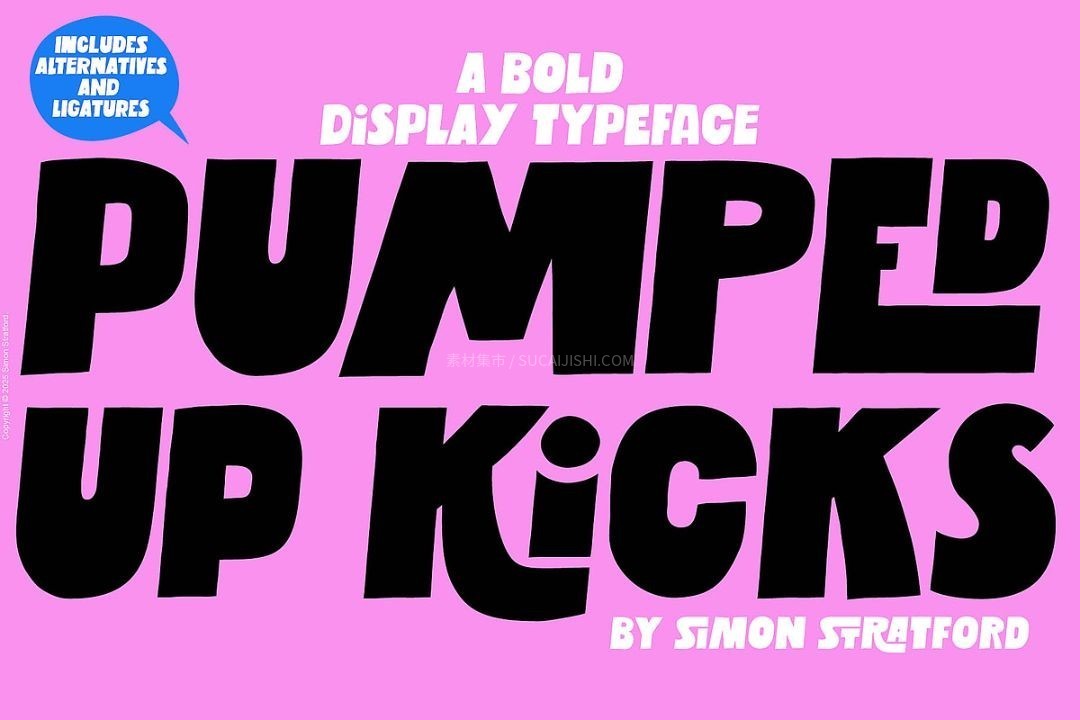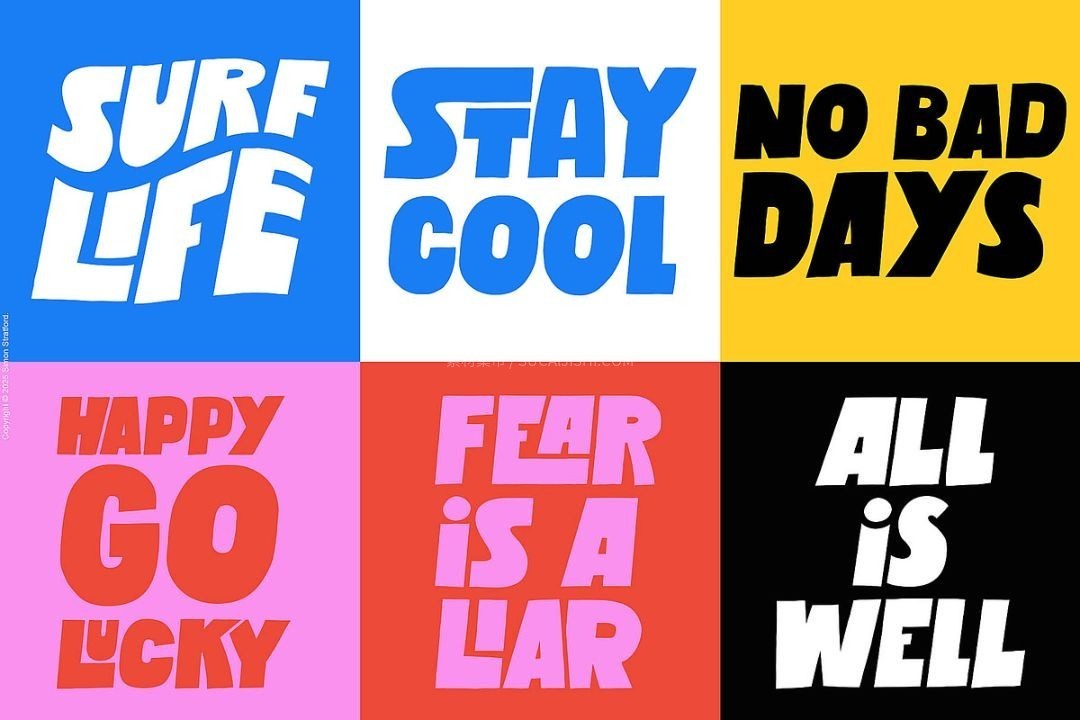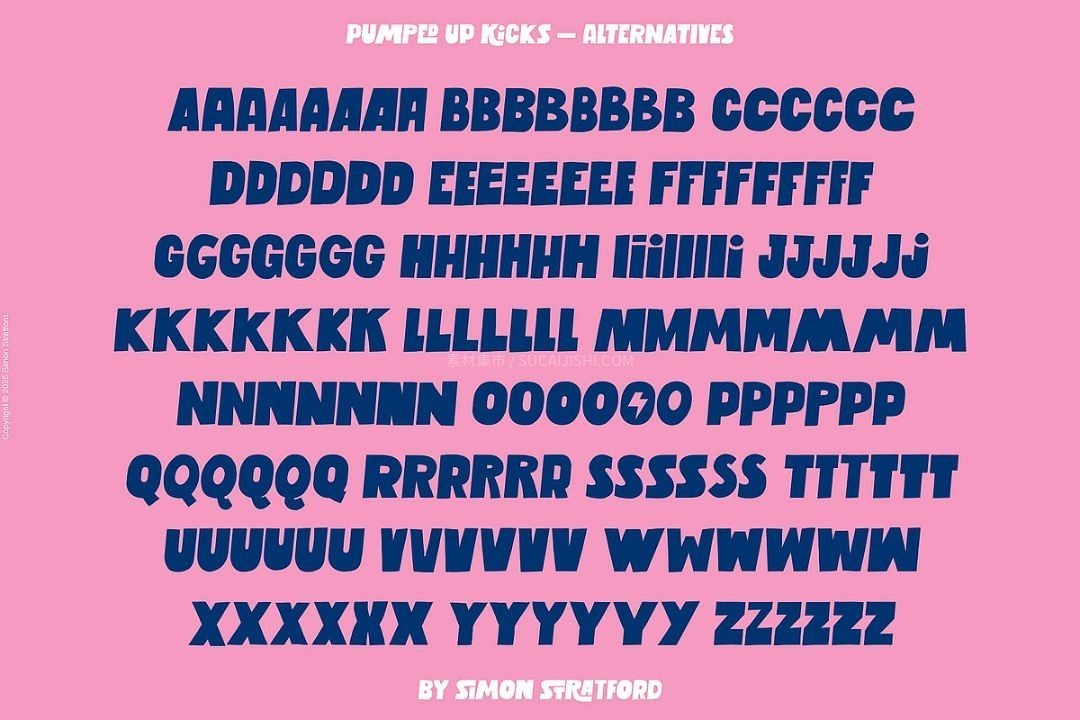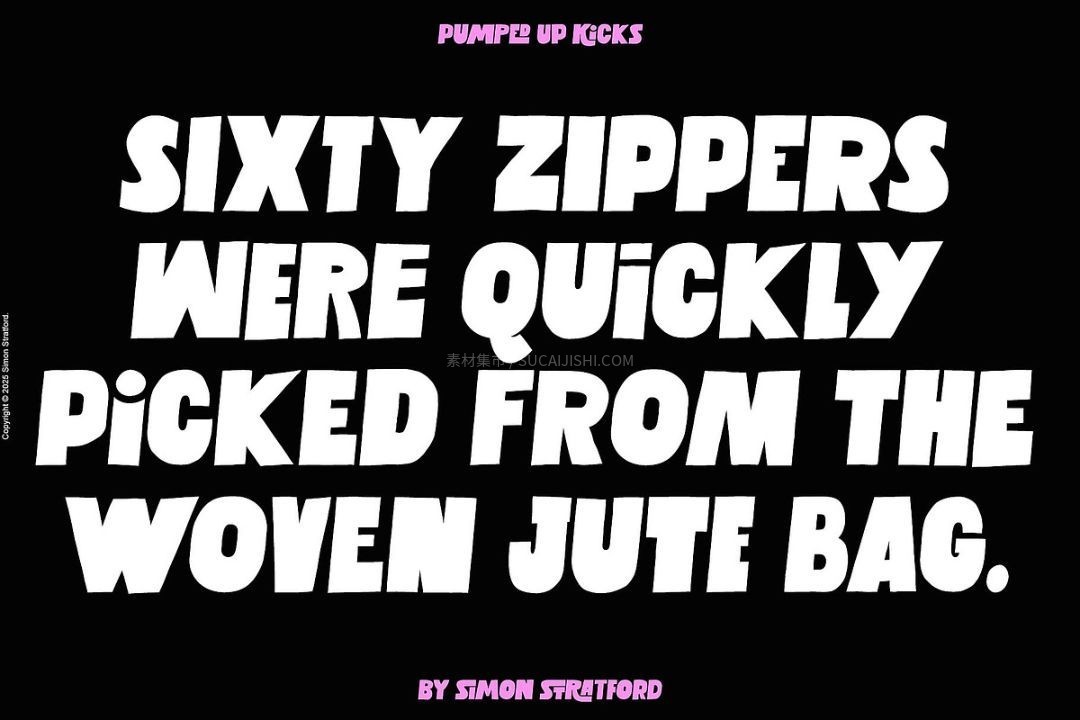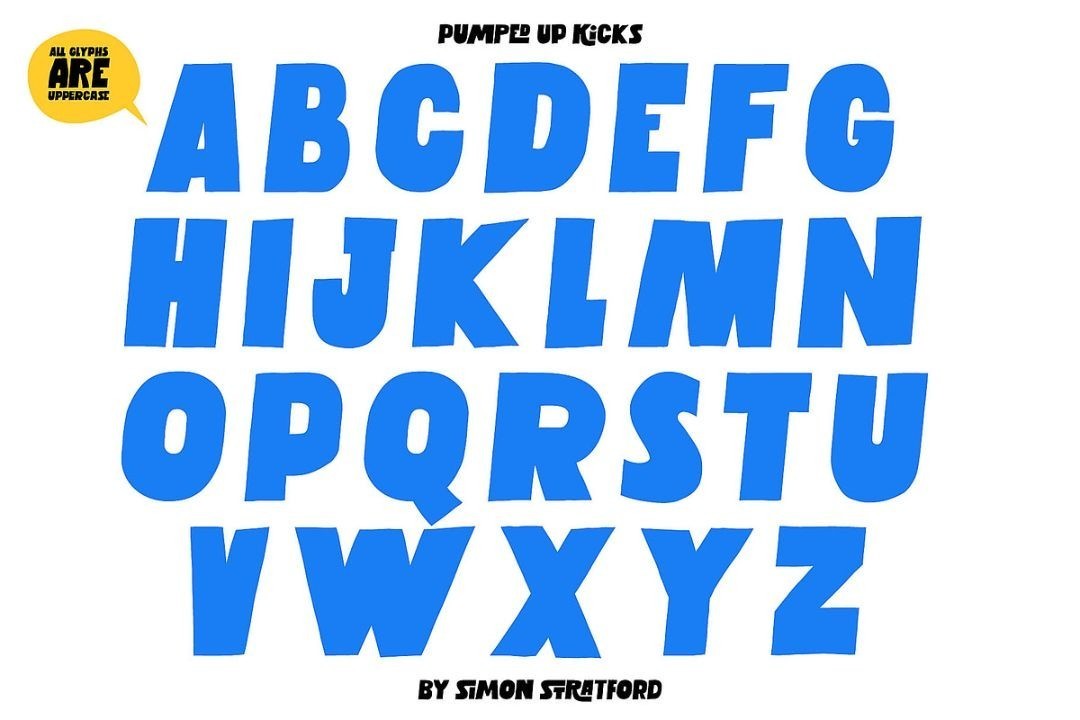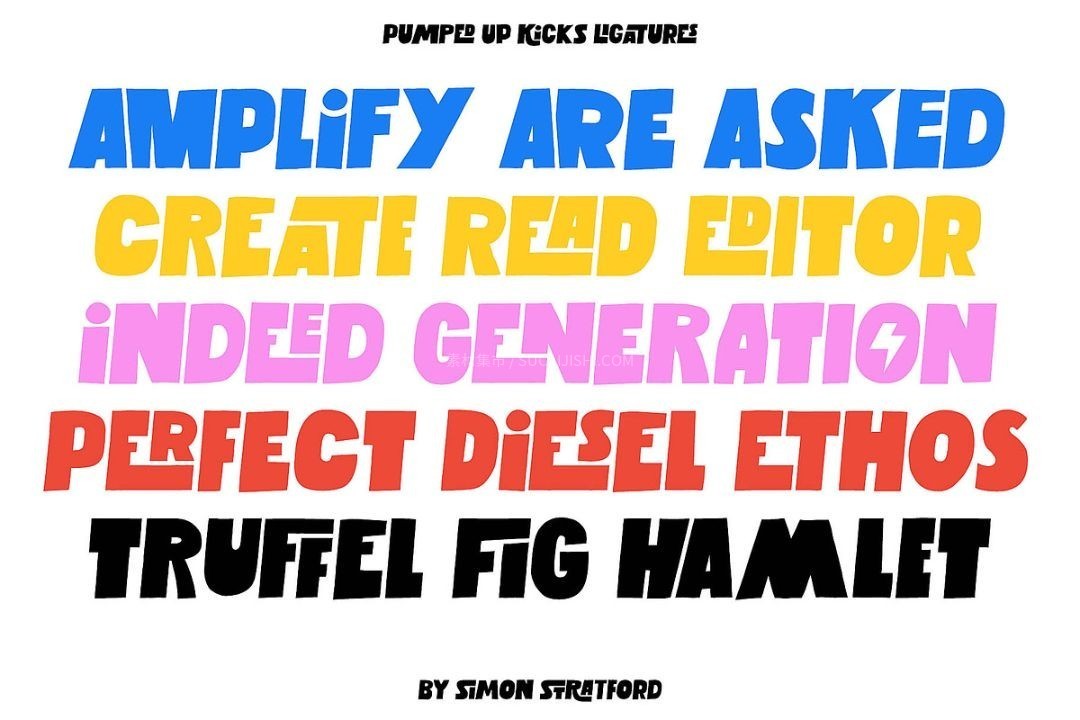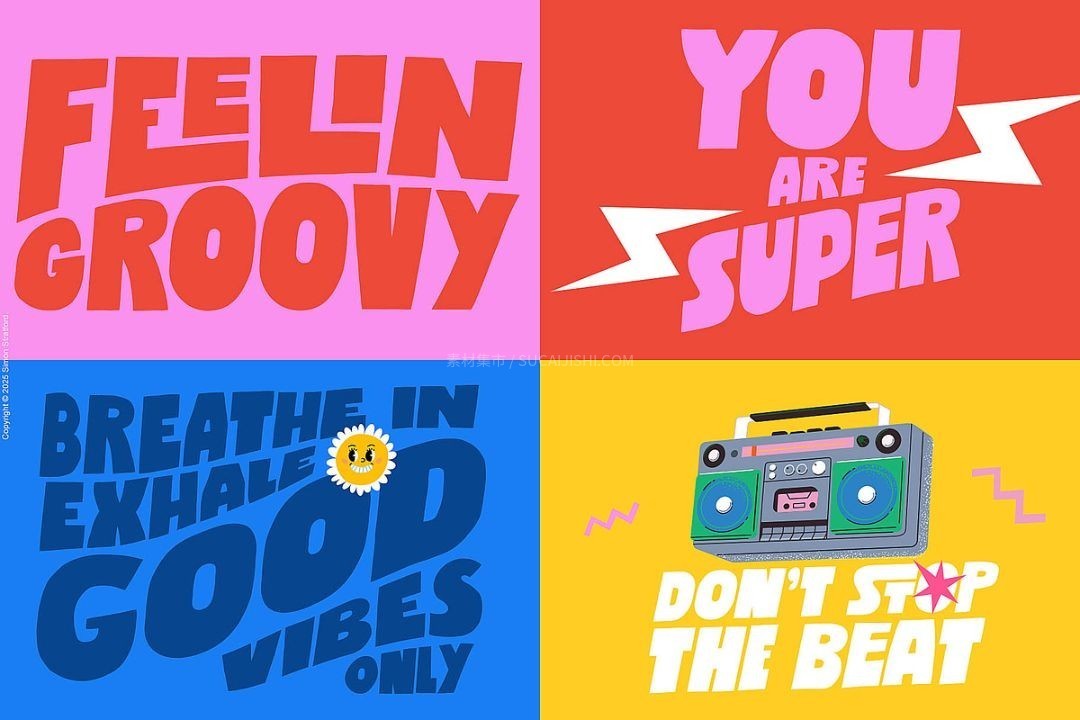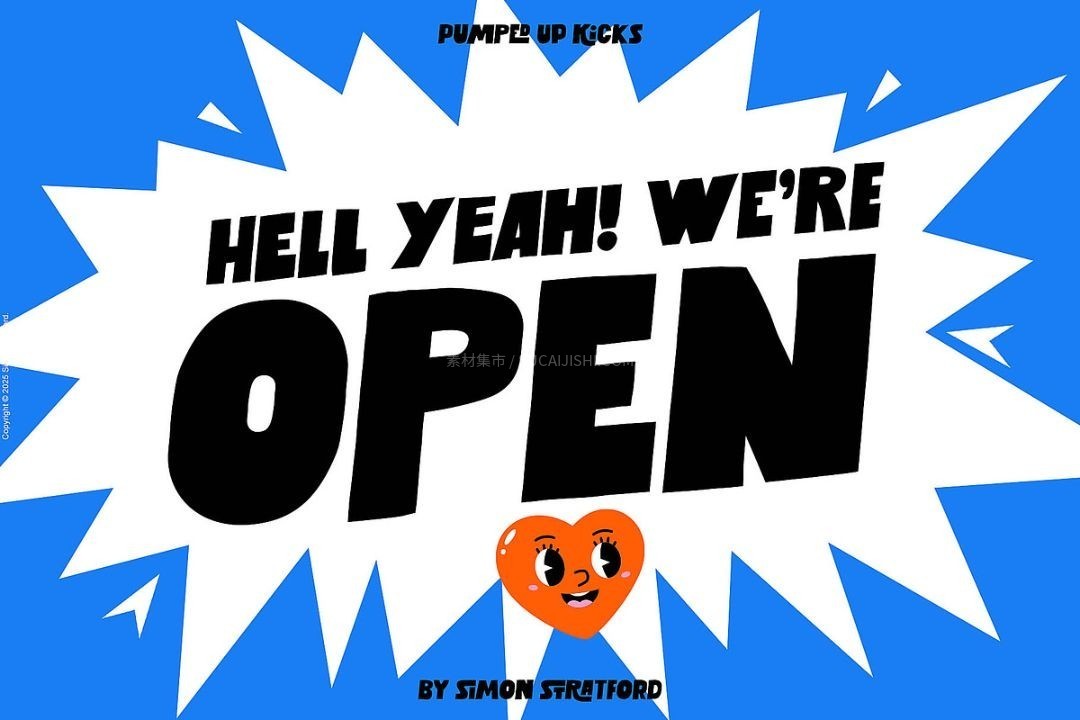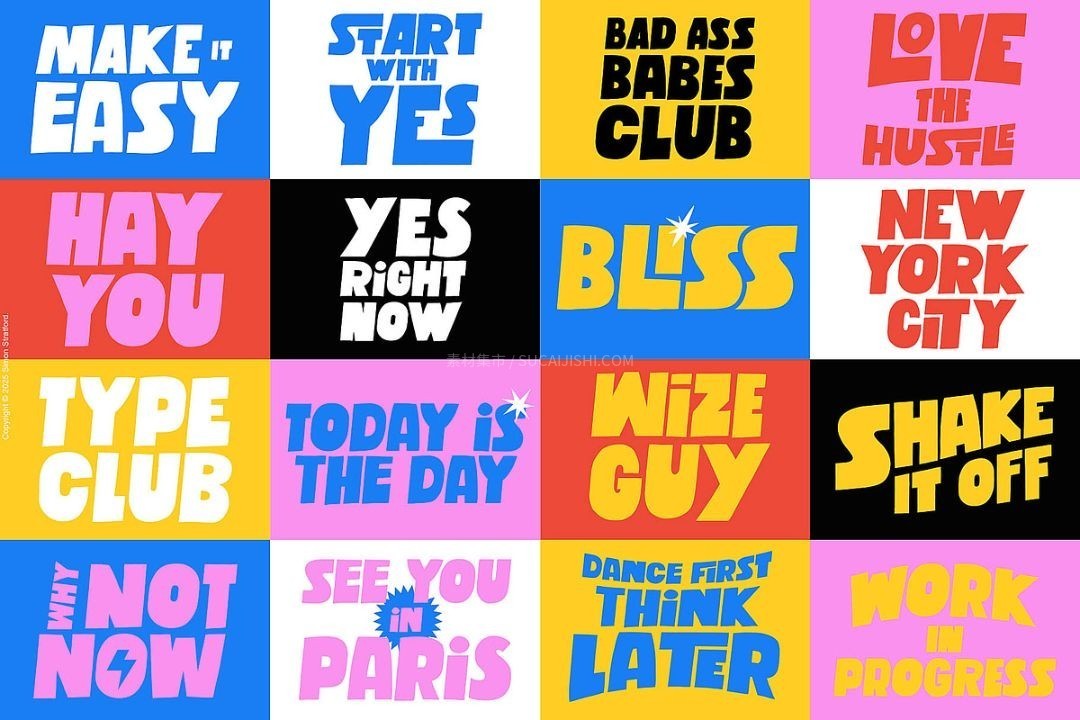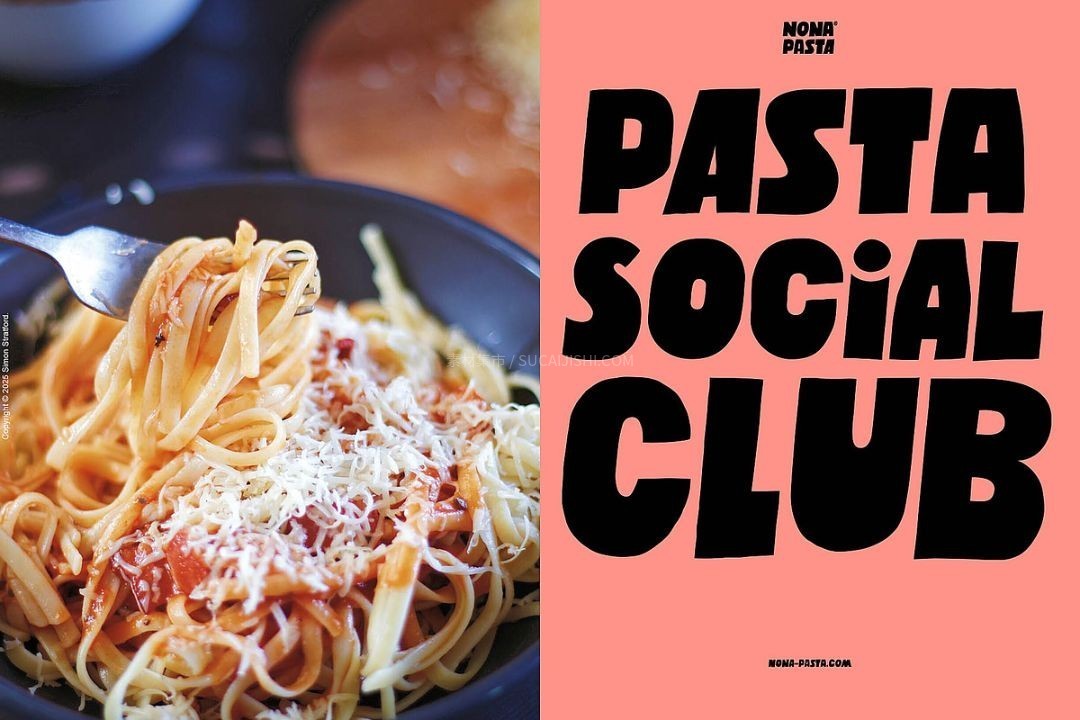
Pumped Up Kicks 趣味跳跃感现代英文字体
一款大胆、活泼且个性十足的无衬线展示字体,自带满满的活力与生机。这款字体最大的亮点在于它“跳跃”的排版效果——硕大清晰的字形搭配微微不规则的线条,部分字母调皮地高低错落于基线上下,带有一种非常自然、俏皮的手工质感。作为一款全大写字体,它还贴心地在小写键位内置了不同的替代大写字形,让你可以轻松组合出更丰富、更具视觉趣味性的创意排版!
Pumped Up Kicks 趣味跳跃感现代英文字体
A 到 Z 提供了超多替代字形,大多数字母至少有 3 款变化,有的甚至多达 7 种!比如单词里有两个“A”,你可以轻松替换成不同的样式,动感和独特性瞬间拉满。不仅如此,它还自带超酷的连字功能(输入大写即可激活,像“LO”、“RA”等组合都有专属设计),给排版增添了满满的手工定制感。只需在设计软件里开启 OpenType 功能,就能轻松解锁这些神仙玩法,让你的设计作品轻松脱颖而出!
Pumped Up Kicks 趣味跳跃感现代英文字体
拿去给宠物医院做科普易拉宝的主标题,轻松活泼又不会显得太随意。